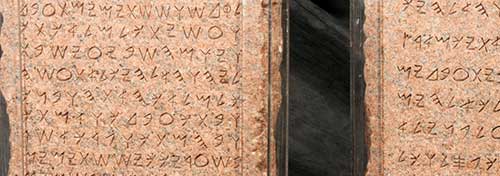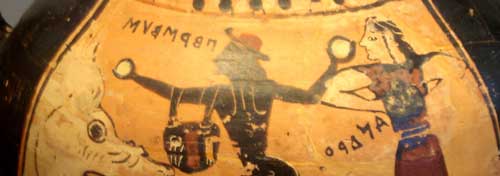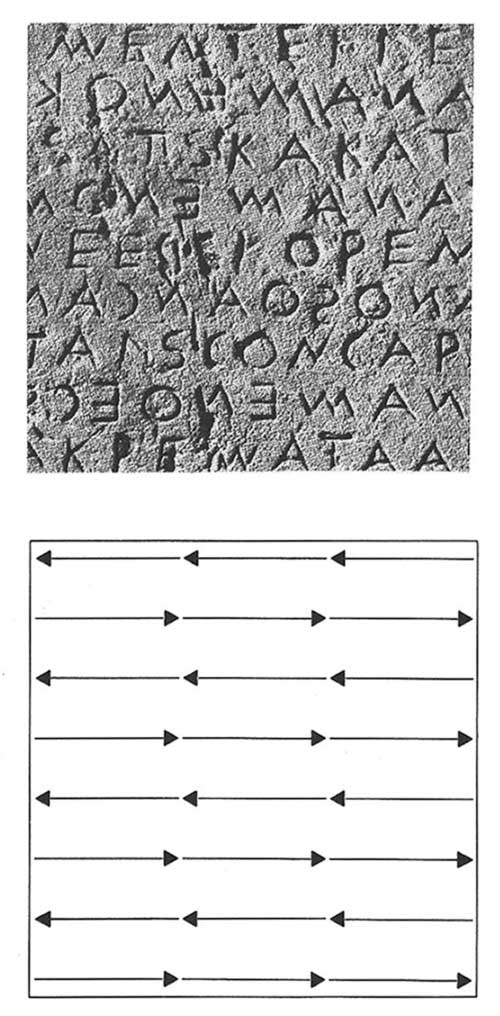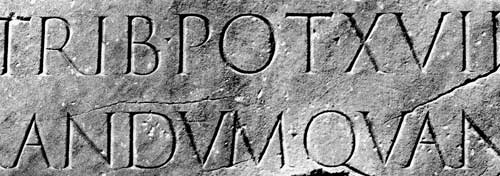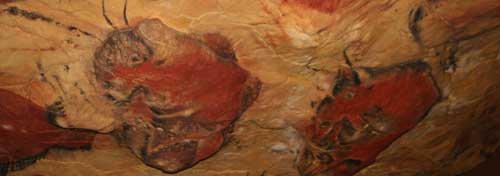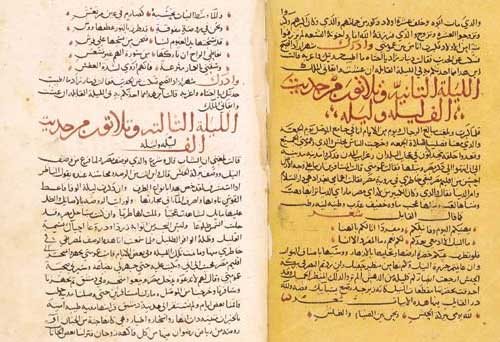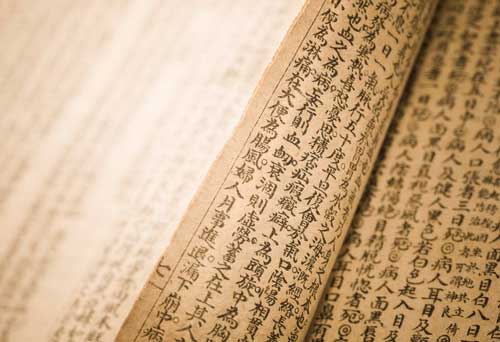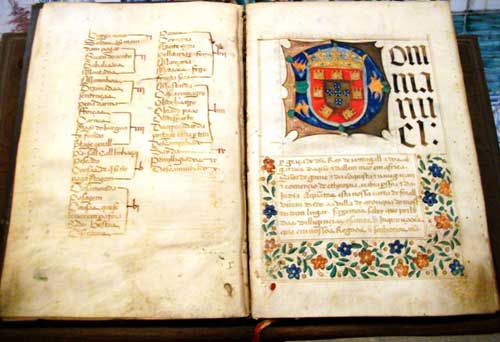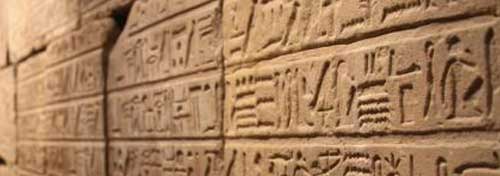
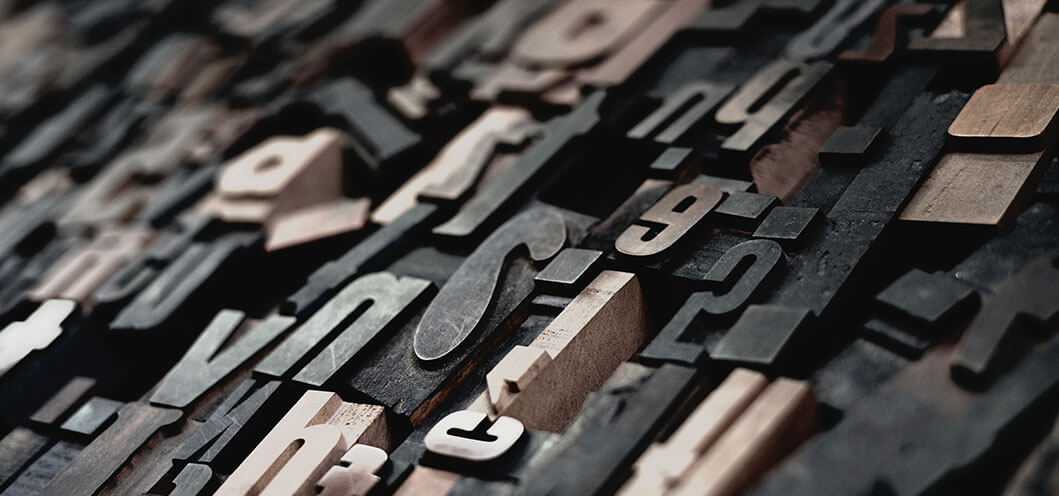
HISTÓRIA DA ESCRITA À TIPOGRAFIA - PARTE 1
Conhecer o porque da existência de coisas, entender a realidade e necessidades das pessoas em épocas passadas auxilia muito quando se quer entender a fundo um determinado assunto e até mesmo criar com base em algo já existente, por isso resolvi escrever esse "breve" artigo (risos) que dividirei em duas partes para contar um pouquinho sobre história e como chegamos ao que temos hoje.
PRÉ-HISTÓRIA: 160.000 À 4.500 A.C.
O período pré-histórico inclui todas as fases das atividades do homem com a prioridade de desenvolvimento da escrita e criação das primeiras cidades.
Os primeiros indícios da necessidade de se comunicar por meio da escrita aconteceram ainda na história glacial em Altamira (Espanha), entre 16.000 e 12.000 a.C., os homens pintavam nas cavernas situações do dia a dia, por exemplo: cenas de caça. Somente milênios a frente (entre 5.500 e 2.300 a.C) com o surgimento de civilizações complexas na Mesopotâmia e Egito é que o método de escrita e a transmissão de informações finalmente começou.
MESOPOTÂMIA: 3.700 À 332 A.C.
Entre 3.500 e 3.200 a.C, os sumérios desenvolveram a escrita cuneiforme. Originalmente derivada de pictogramas, os caracteres eram desenhados através do abstrato: ideogramas, fonogramas e outros fatores determinantes. Usando materiais de madeira em forma de cunha, os escribas pressionavam os caracteres em tabuletas de argila mole que depois eram secas e cozidas, por esse motivo foram preservados muitos documentos daquele período.
EGITO ANTIGO: 3.150 À 332 A.C.
Entre 3.000 e 2.665 a.C., o rei Menes foi creditado por inventar a escrita e unificar o império, a essa escrita foi dado o nome de hieróglifos, os hieróglifos eram inicialmente usados para marcações em túmulos e templos.
Com o passar dos anos e com a criação do papiro em 1.520 a.C. a escrita começou a ser pintada o que tornou os hieróglifos mais bonitos e facilitou o transporte. Devido a quantidade muito grande de hieróglifos criados (mais de três mil), esse tipo de escrita foi extinguido.
FENÍCIOS: 1.200 À 539 A.C.
Os fenícios sobreviveram ao domínio de vários impérios e dominaram o comércio na Mesopotâmia. Devido a manterem contatos comerciais com diferentes povos, sentiram a necessidade de facilitar a comunicação, e fundaram o alfabeto fonético que, entre 1.200 e 730 a.C., viajou por toda a sua rede que conectava povos da Inglaterra à Grécia. O alfabeto que criaram era composto por 22 sinais que foram aperfeiçoados e originaram o alfabeto grego.
GRÉCIA ANTIGA: 1.500 À 146 A.C.
O alfabeto grego foi criado por volta do ano 800 a.C. a partir da adaptação do alfabeto fenício e é utilizado até hoje no grego moderno e em algumas ciências como Matemática, Física e Astronomia. Esse alfabeto era composto de 24 letras - vogais e consoantes.
ROMA ANTIGA: 753 A.C. À 395 D.C.
O alfabeto romano-arcaico foi criado por volta de 300 a.C. baseado indiretamente no alfabeto grego, esse alfabeto possuía cerca de 21 letras - vogais e consoantes - todas escritas em letra maiúscula.
Inicialmente as letras romanas eram escritas sem acabamentos terminais, porém com o aperfeiçoamento das ferramentas para talhar a pedra, é que surgiram as terminações designadas serifas ou patilhas. Importante ressaltar que as letras romanas apresentavam também contrastes de grossura.
Somente anos mais tarde, com o surgimento da escrita cursiva é que passou a se usar as letras minúsculas. A letra cursiva surgiu da necessidade de acelerar a escrita de alguns documentos, para evitar problemas de legibilidade as letras ganharam hastes ascendentes e descendentes.
IDADE MÉDIA: 476 À 1.453 D.C.
Na Idade Média começaram a surgir uma série de diferentes tipos de fonte. Nesse período existiu uma presença marcante dos monges copistas que escreviam e copiavam manualmente os livros, foi na Idade Média que surgiram diferentes tipos de fontes, muito diferentes das utilizadas na Roma Antiga, cursivas, ornamentadas, pois para eles a escrita empregada na Roma Antiga era considerada pagã.
Os títulos bem como as letras que iniciavam uma página ou capítulo eram enfeitados ao extremo de forma bastante variada: com figuras humanas (antropomórfica), motivos animais (zoomórficas) ou até mesmo ornamentos baseados nos entrelaçados irlandeses.
A medida que os manuscritos foram aumentando, crescia também a necessidade de tornar a escrita uniformizada, inteligível. A letra minúscula foi a melhor opção para atingir esse objetivo.
Por volta do século XI foi criada a fonte gótica. No século XV percebeu-se que a fonte gótica tinha melhor aplicação em textos litúrgicos e então foi desenvolvida uma fonte mais condizente com a simplicidade requerida pelo uso diário: a bastarda.
ALGUMAS CURIOSIDADES
- Os chineses e japoneses escrevem da direita para a esquerda e em colunas.
- Os árabes também escrevem da direita para a esquerda, porém em linhas de cima para baixo.